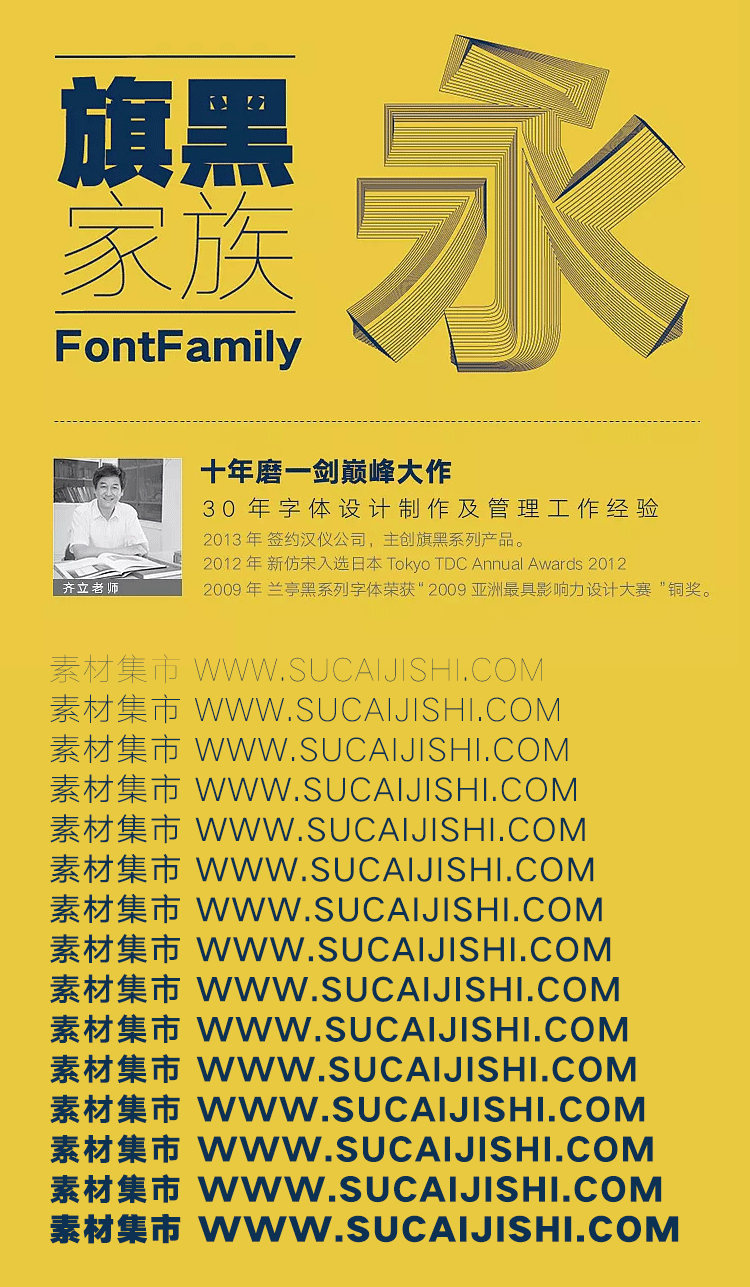
汉仪旗黑全套字体
汉仪旗黑字体是汉仪字库推出的一款庞大而完整的家族字体(据称是由微软雅黑、方正兰亭黑的主设计师齐立主导设计的),汉仪旗黑共由三个系列字体(长、方、扁)组成,从最细的25到最粗的105,共计15个字重,是迄今为止国内最大、最丰富的字重的家族字体,可以满足企业多渠道,全方位的内容设计以及定制化需求,实现企业品牌形象在各渠道的统一呈现。